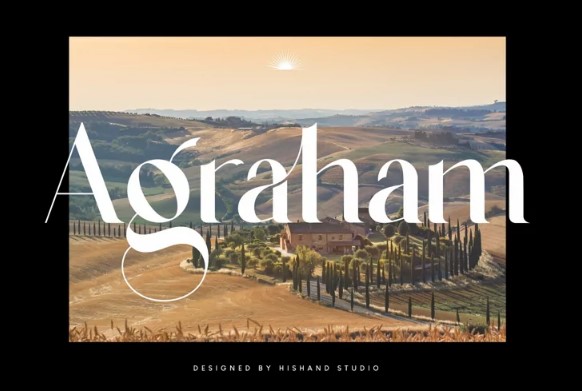
Fontbundles Agraham Serif Font 2021
[Fontbundles] Agraham Serif Font (2021)
Agraham - эстетический шрифт с засечками, вдохновением для которого послужили уникальные итальянские вибрации и небольшое прикосновение к красоте Парижа, Франция. Он идеально подходит для логотипов, упаковки продукции, рекламы, постов в социальных сетях, модных брендов, заголовков журналов и многого другого.